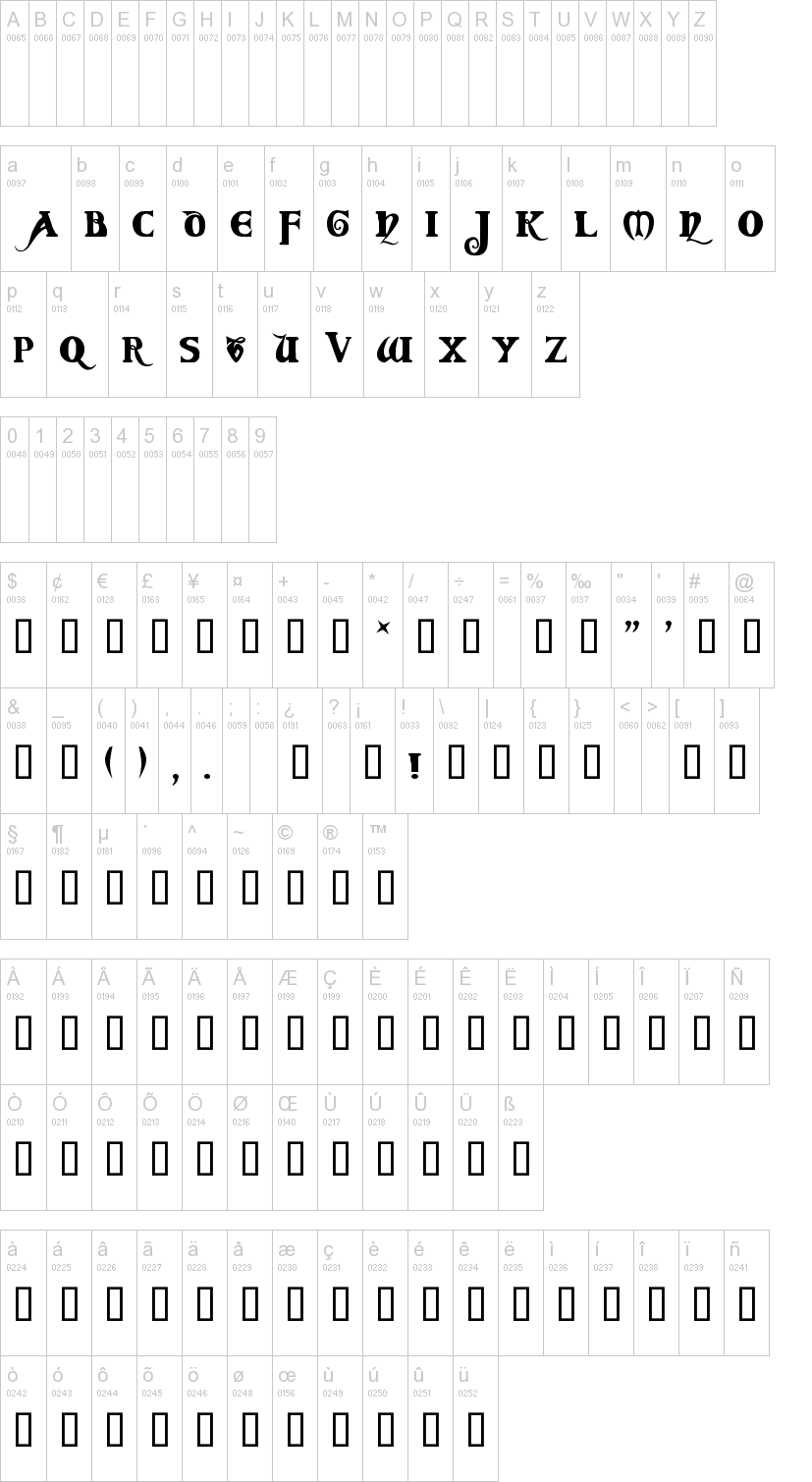
Coverack 是一款非常漂亮的手写风格字体,由英国设计师 Tom Chalky 创作。这款字体灵感来源于英格兰南部海岸的一个小镇,也被命名为 Coverack。 Coverack 字体有一种自然、柔和和流畅的感觉,适合用于印刷品、包装、品牌标识、海报、广告和网站设计等多种用途。它包含了英文大写字母、小写字母、数字和标点符号,还带有一些特殊字符和连字。 这款字体还有一些变体,包括 Coverack Bold 和 Coverack Italic,可以让设计师更加灵活地应用在不同的设计场景中。总的来说,Coverack 字体是一款非常时尚、优雅且有个性的字体,非常适合现代化的设计风格。内容介绍
Coverack是一款非常不错的手写艺术字体,具有很好的视觉感,适合于文化类的宣传设计、商业类品牌的广告和产品包装设计以及个性化文字排版等较多场景。